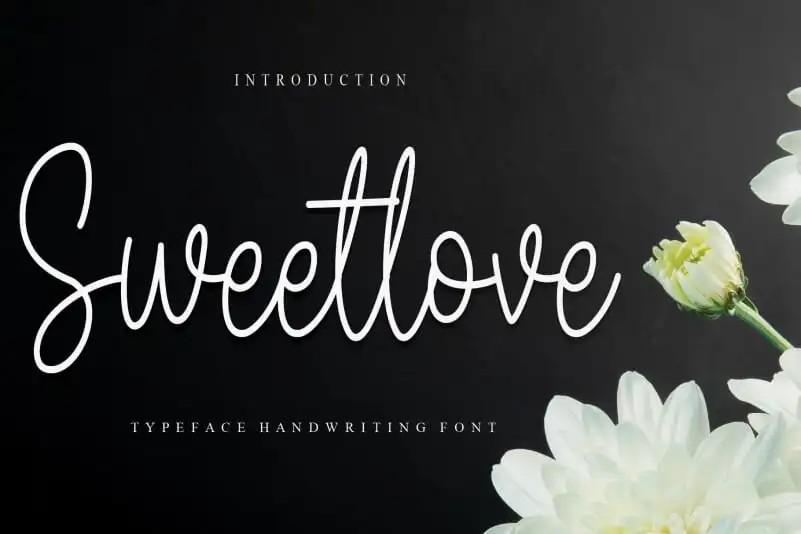
Sweetlove Script Font – Download Grátis
A Sweetlove Script Font é uma deliciosa escolha para quem busca um estilo elegante e sofisticado nas suas criações digitais. Com traços finos e leves, essa fonte à mão levanta a cabeça dos textos mais simples ao texto personalizados com grande destreza. Ideal tanto para escrita de blog, como para uso em design gráfico, a Sweetlove Script traz uma experiência única e especial que irá encantar seus usuários. É perfeita para projetar cartazes, identidades corporativas ou qualquer outro tipo de material visual que exija um acabamento cuidadosamente detalhado. Ideal tanto para profissionais quanto para designers iniciantes que buscam adicionar um toque autêntico e único ao seu trabalho, a Sweetlove Script é uma fonte à mão perfeitamente adequada para a categoria de Handwritten Fonts. O designer criativo responsável pela Sweetlove Script não mediu esforços para desenvolver este produto único, garantindo que cada caracter exiba um nível de personalidade e estilo inigualável. Para aqueles que buscam uma adição única ao seu projeto, esta é a fonte à mão que você precisa.